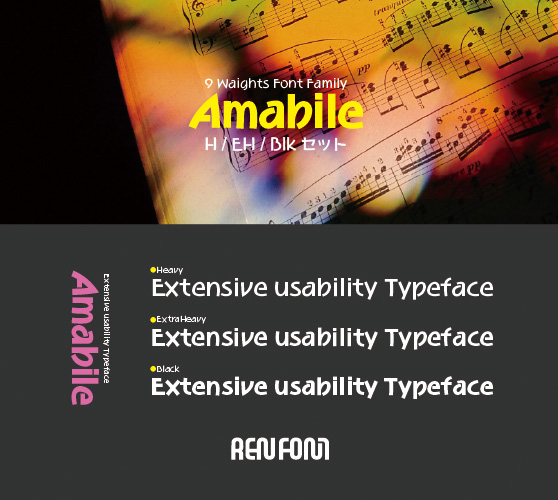
Amabile-タイトル・大見出し用3ウェイトセット(H/EH/Blk)
愛らしく親しみやすい多言語欧文フォント
この書体の名前は「Amabile(アマービレ)」。音楽用語で「愛らしく」という意味があります。「和音」の従属欧文として制作された性格上、当然ながら「和音」の特長を反映したデザインになっています。「和音」の基本コンセプトである「文字で音楽を表現する」を、最も端的に文字通り「表現」しているのがこの「Amabile」です。
そして、W1Gの規格にプラスアルファし、87か国言語を表現できる多言語フォントに生まれ変わりました。
ほとんどの和文書体の従属欧文は Latin, Cyrillic, Greek の3種類が基本です。「Amabile」はこの3種類に Latin 補助、Cyrillic 補助、Greek 補助、Latin 拡張などを加えた、いわゆるW1Gの規格にプラスアルファし、87か国言語を表現できる多言語フォントに生まれ変わりました。
グリフ形状は、比較的自由にデザイン表現が可能な Latin 以外は「Amabile」の特徴を残しつつ、ネイティブの形状を壊さない、ぎりぎりの選択を施してあります。タイトル・大見出し用3ウェイトセット。